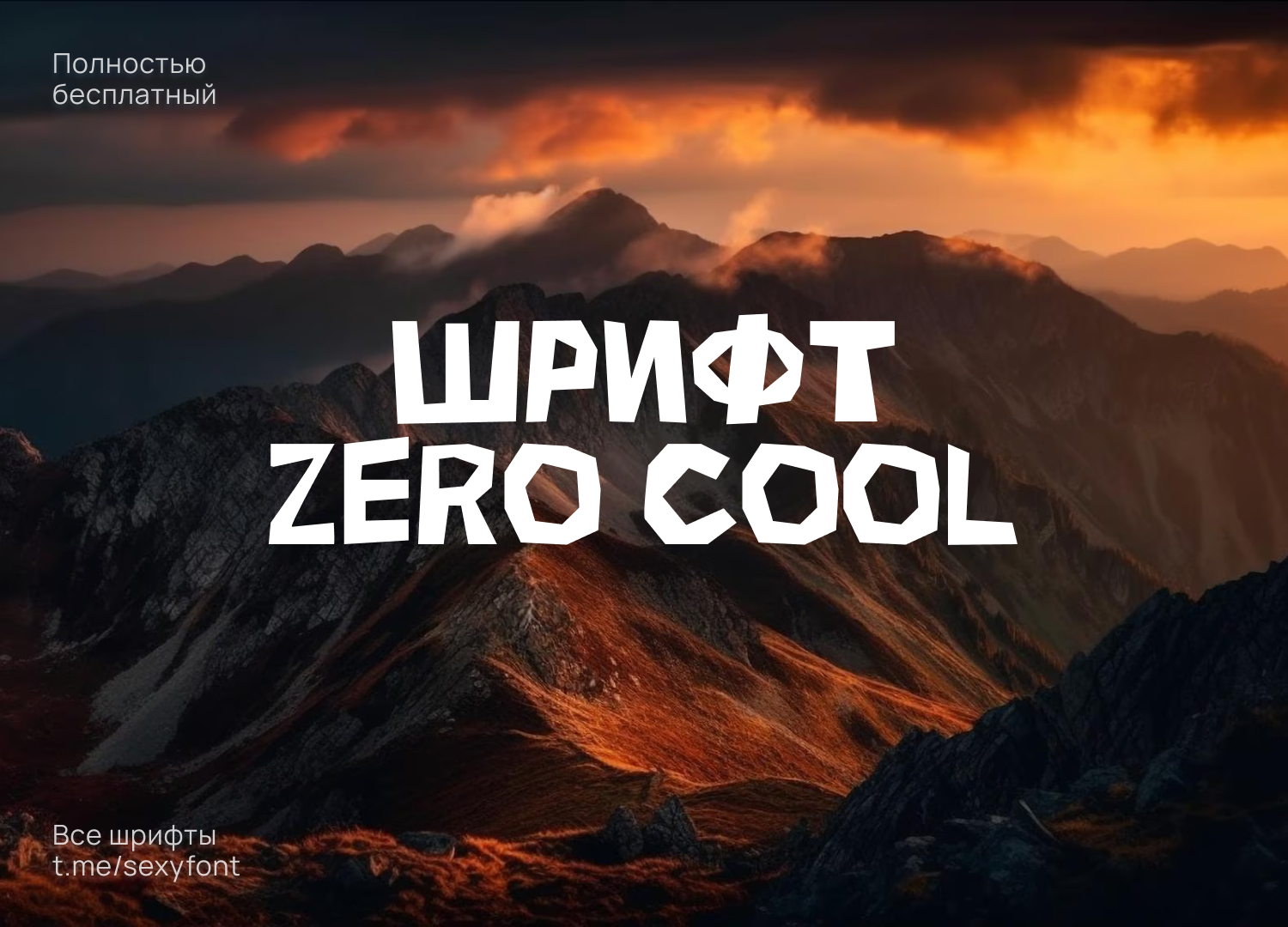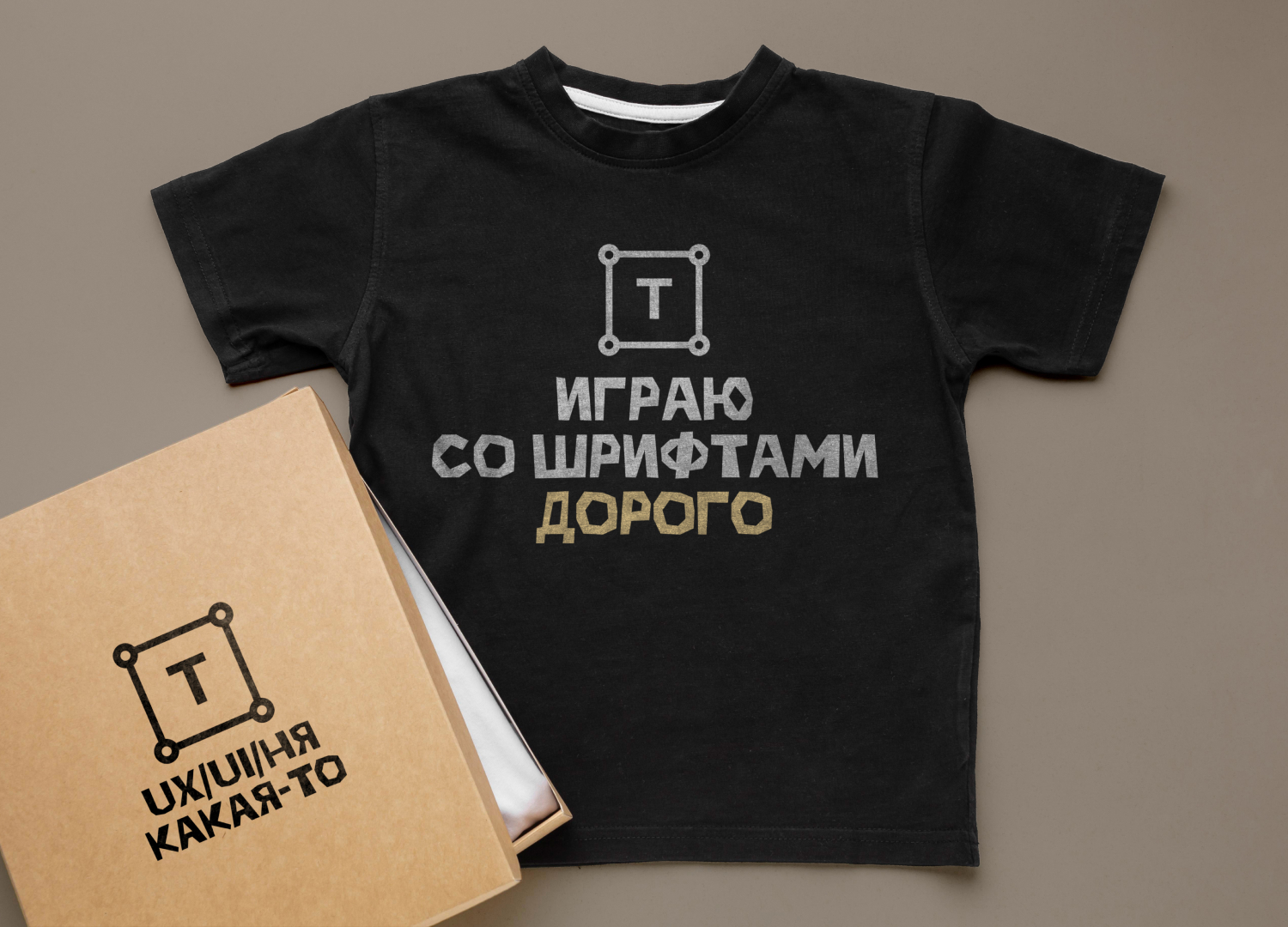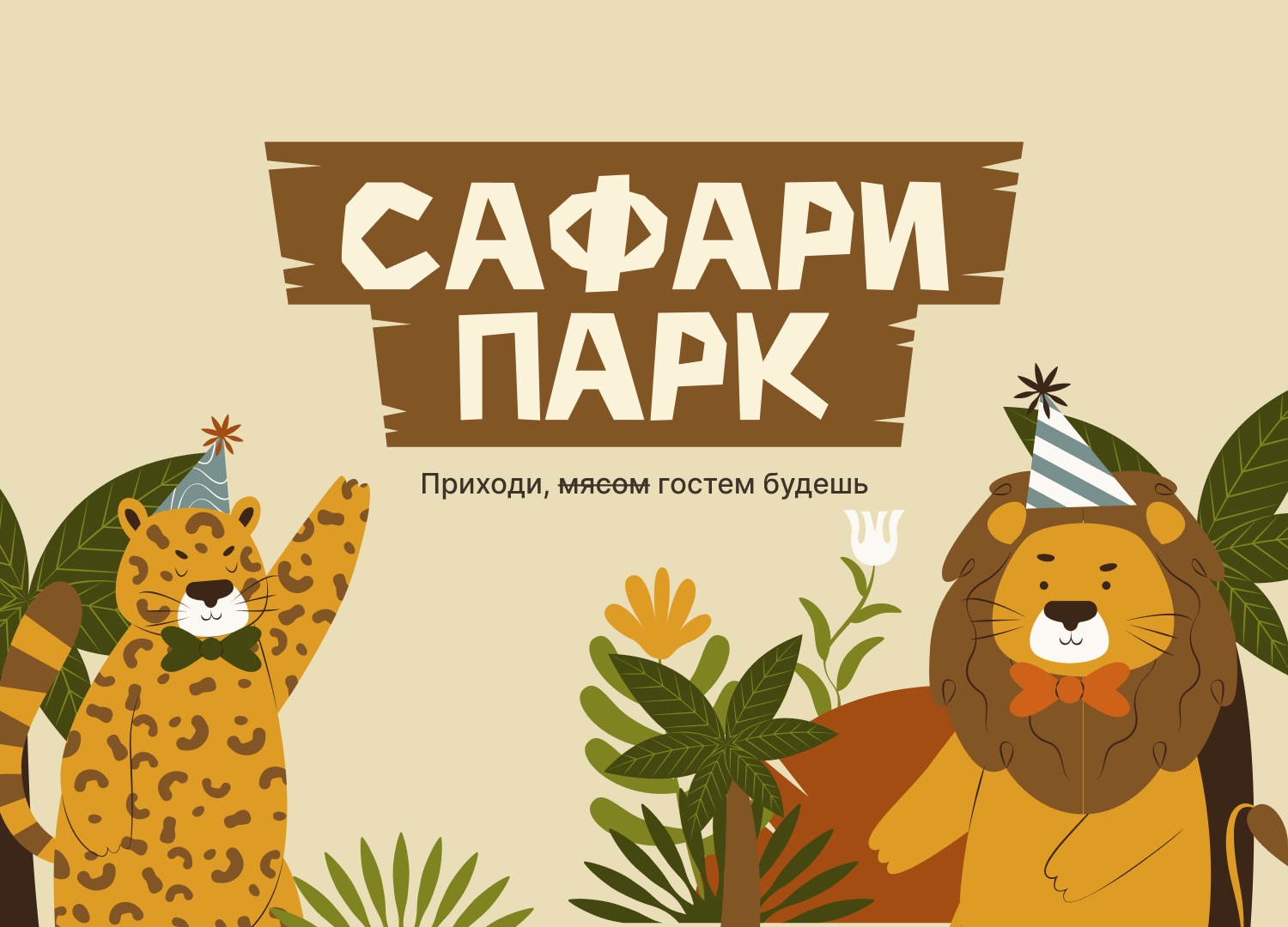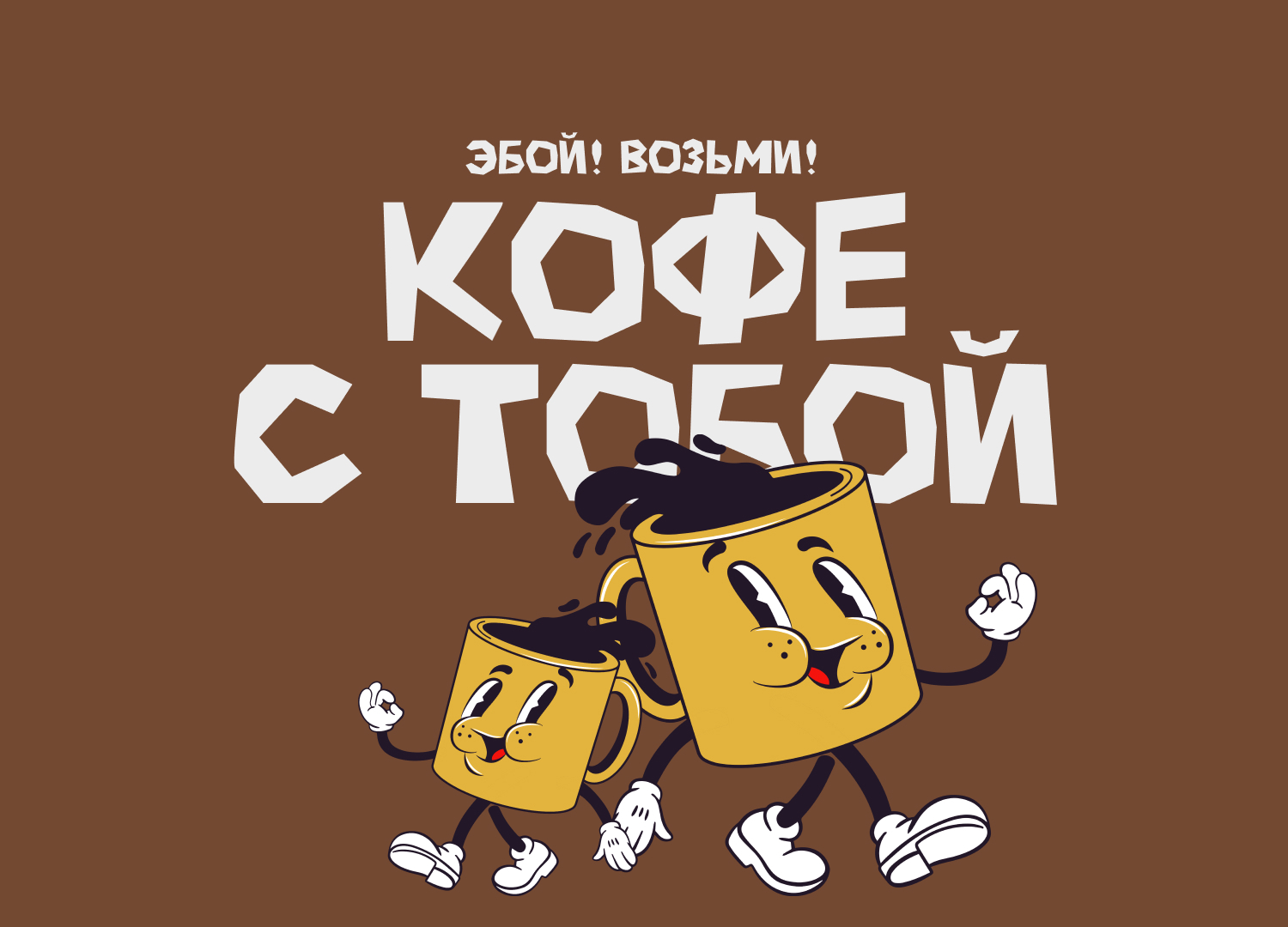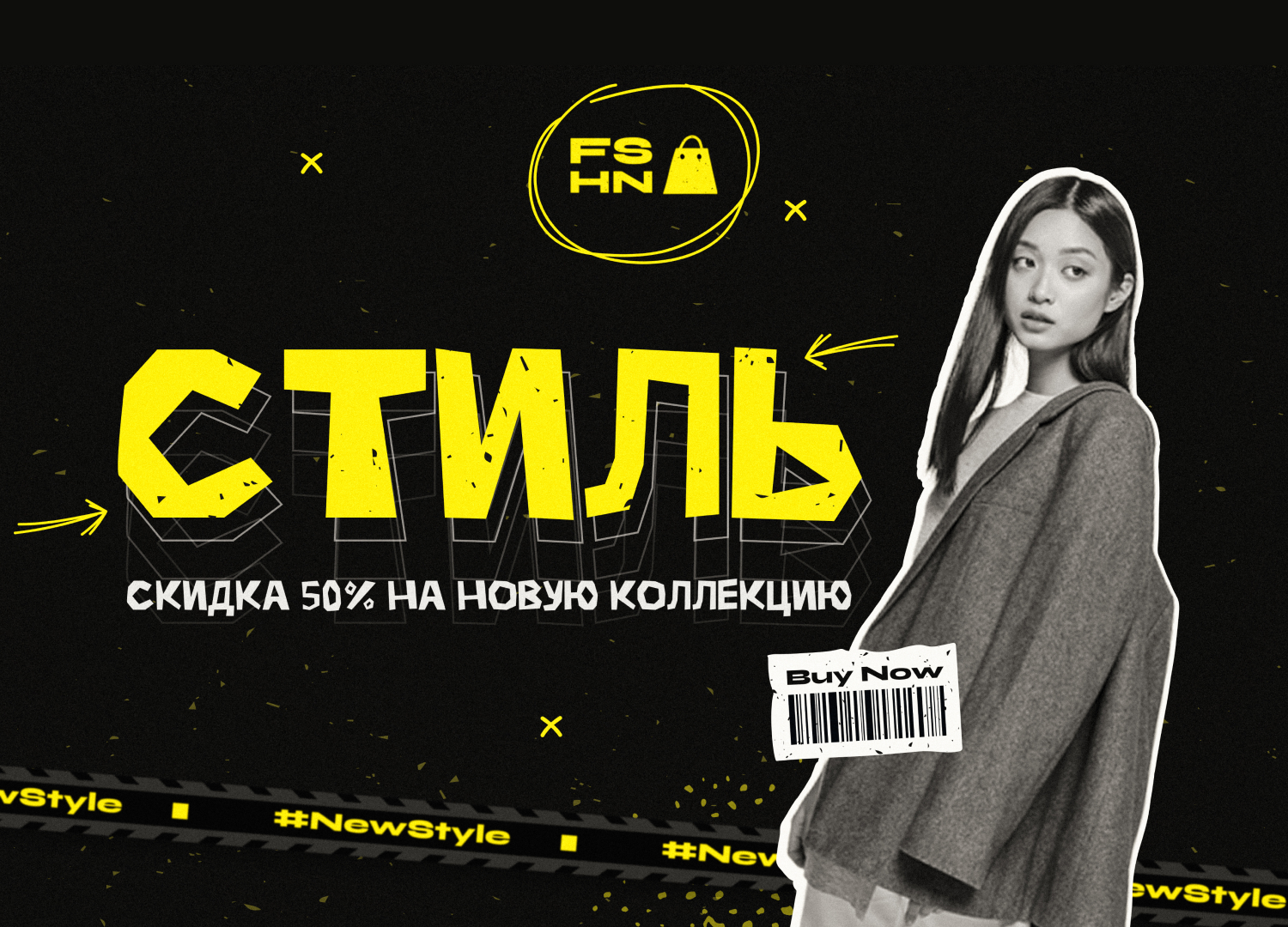
Шрифт zero cool
Доделал новую презентацию) Zero cool. Декоративный, остроугольный и немного играющий шрифт. Бесплатно для личного и коммерческого использования. Спасибо за плюсы на прошлые посты) Огонь накидали.